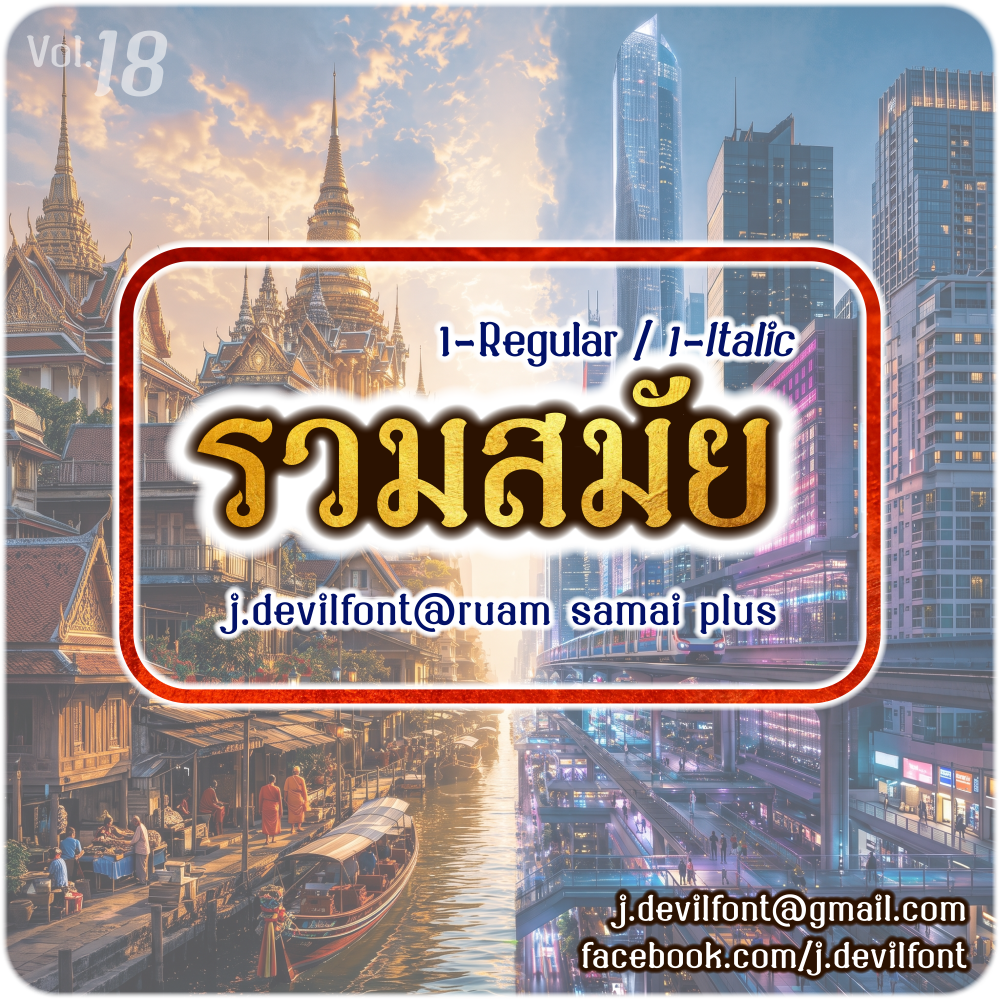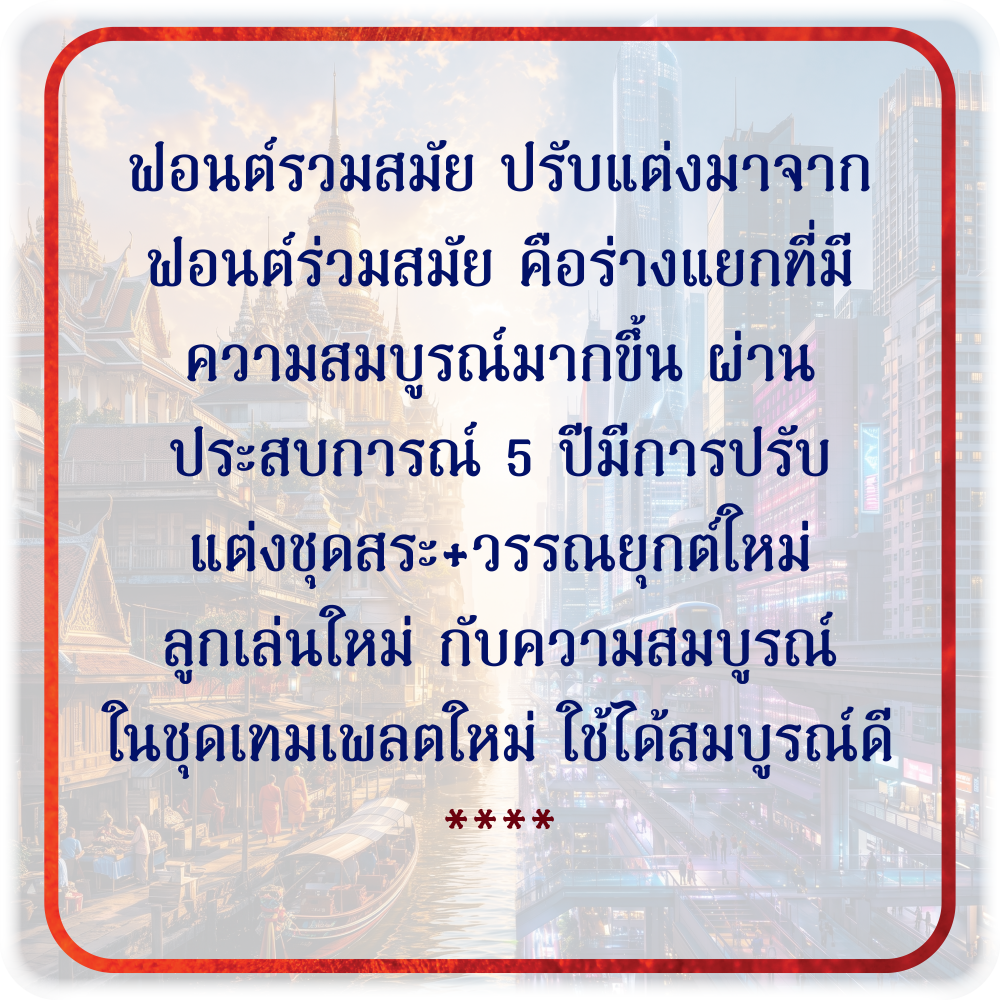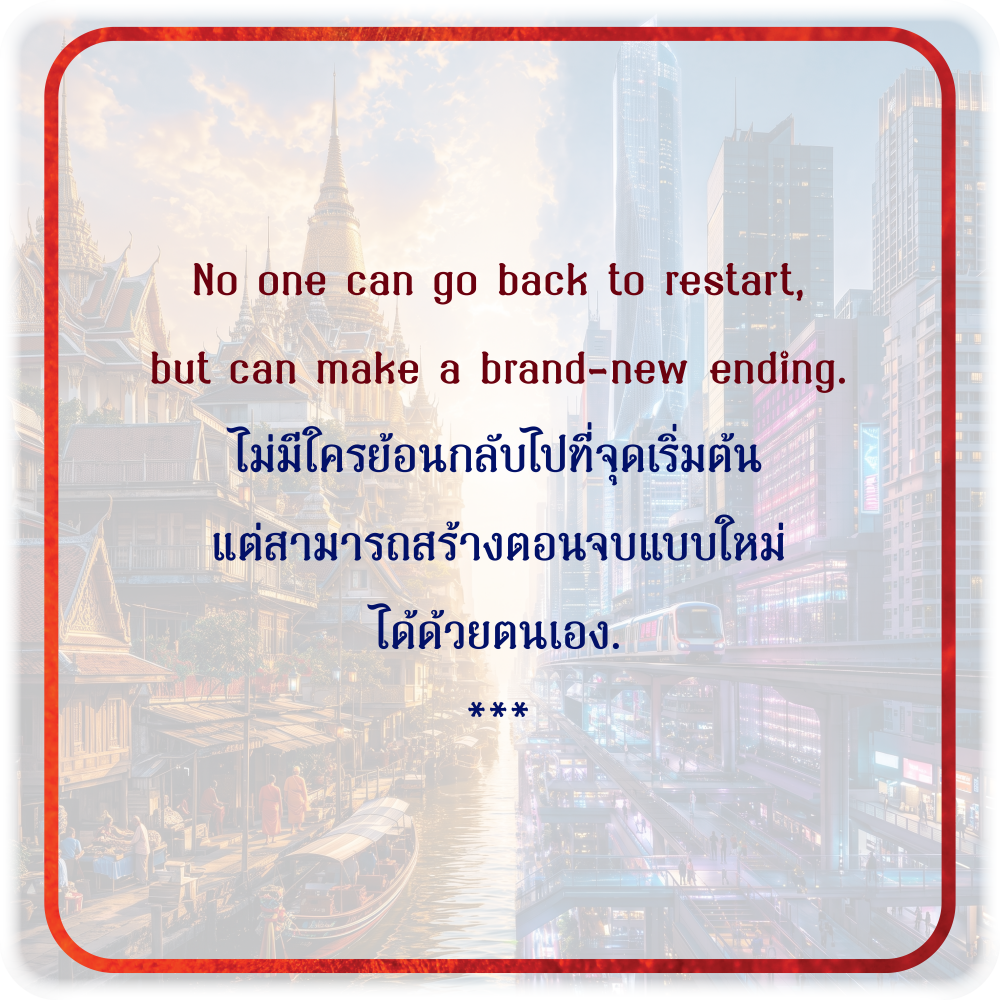
ฟอนต์เรเชล ( Rachel ) – แจกฟรี เวอร์ชันสำหรับทดลองใช้งาน (Demo)
ไฟล์แจกฟรี  (Demo) เป็นเวอร์ชันทดลองใช้งาน ยังไม่ได้ปรับสระ
ตัวอักษรบางส่วนอาจมีไม่ครบ อักษรใส หรือขนาดไม่เท่ากัน หากต้องการใช้งานแบบเต็มประสิทธิภาพ แนะนำให้ซื้อเวอร์ชันเต็มค่ะ✨
พิกัดฟอนต์ฟอนต์ดรีมมี่ (PKF-dreamy)
ชอบแนวยุ๊กยิ๊กๆ ต้องไม่พลาดฟอนต์นี้
ฟอนต์เอฟซี มีสกุล เซอริฟ (FC Mee Sakul Serif)
ฟอนต์คู่แฝดมีเชิงไม่มีเชิงตระกูลมีสกุล
ฟอนต์ดีไอวาย (KT-DIY)
ฟอนต์สไตล์กึ่งทางการ มินิมอล
SP_Thepharak เทพารักษ์
ฟอนต์เทพารักษ์ เป็นฟอนต์ที่อยู่ในโครงการอักษราสูตรไทยวิจิตร มุ่งเน้นการออกแบบลายเส้นให้กลมกลืนกับศิลปะลวดลายไทย
จัดรูปแบบอักษรให้เป็นเอกลักษณะเฉพาะตัว เข้ากันกับชุดอักษรนั้นๆ รวมถึงอักษรภาษาอังกฤษและสัญลักษณ์อื่นๆครบถ้วนบริบูรณ์
พร้อมใส่ฟีเจอร์ (แก้สระลอย-ล็อกเป้าเข้าพิกัด) เพื่อความสวยงามและลงตัว ไม่ว่าจะเป็นช่องไฟ สระวรรณยุกต์ ชั้นล่างชั้นบน
และแยกนิคหิตเพื่อการใช้พิมพ์ภาษาบาลีไห้ถูกต้องตามหลักไวยากรณ์ ภายในฟอนต์ๆเดียว (Microsoft-Adobe ต้องเปิดค่ารองรับ)
ฟอนต์อักษรวิจตรชุดนี้ เหมาะสำหรับงานออกแบบเฉพาะด้าน เช่น โลโก้ ป้ายชื่อ สิ่งพิมพ์ โฆษณา งานเทศกาลพิเศษอื่นๆ เป็นอาทิ
ทั้งนี้ยังมีพรีเซนต์ข้อความสไตล์เอฟเฟค ในรูปแบบต่างๆเล็กน้อย เพื่อเป็นแนวทางในการใช้งานฟอนต์ ของผู้สนใจทั่วไปด้วย
SP_FONT อักษรวิจิตร มุ่งเน้นสู่คุณค่าเอกลักษณ์ความเป็นไทย ใส่ใจทุกเส้นสายรายละเอียดศิลป์
- ฟอนต์ KanchaEnjoy ฟอนต์ลายมือบรัชเส้นตัด แนวน่ารักๆค่ะ
ออกแบบโดย : เจ.ปีศาจฟอนต์